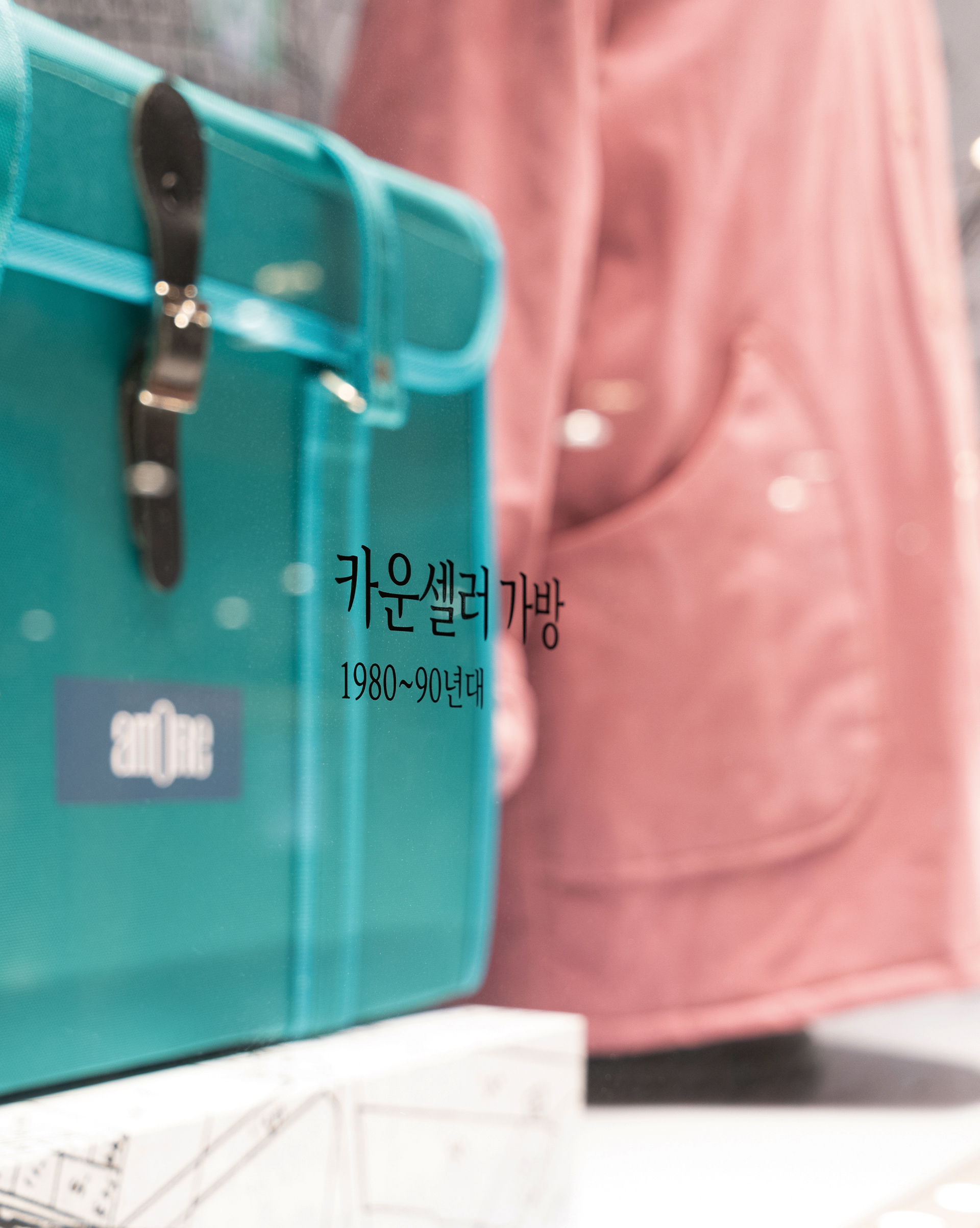
아리따부리 — 아모레퍼시픽에서 배포하는 무료 폰트입니다. 전통 명조의 구조에 현대적인 곡선과 섬세한 부리를 더한 우아한 본문용 세리프체
아리따 가족의 부리 쪽으로, 2012년에 착수해 2014년에 완성하고 2015년 1월에 무료로 풀렸습니다. 글꼴 디자이너 류양희가 맡고 안그라픽스 타이포그라피연구소가 진행했습니다. 여덟 번의 회의와 서른두 개의 스케치 시안을 거쳤는데, 본문 글꼴의 미덕인 보편성과 기업 글꼴에 필요한 개성 사이에서 균형을 찾는 과정이었다고 기록돼 있습니다.
목표는 분명했습니다. 기존 명조체의 예스러운 표정에서 벗어나는 것입니다. 그래서 글자 줄기를 부드럽게 휘고 획의 움직임을 유연하게 풀어, 손글씨의 운동감을 명조 구조 안에 넣었습니다. 파일에서 재어 보면 세로획이 가로획의 2.1배에 이르는데, 이 또렷한 대비가 단아하면서도 선명한 인상을 만듭니다.
굵기는 헤어라인부터 Bold까지 다섯 가지이고, 이 가운데 헤어라인은 국내에서 처음 시도된 굵기로 알려져 있습니다. 2015년 레드닷 디자인 어워드 타이포그래피 부문을 받았습니다. 긴 호흡의 본문을 겨냥한 서체지만 헤어라인은 획이 머리카락처럼 가늘어 작은 크기나 어두운 배경에서는 획이 사라질 수 있으니 큰 크기에서 쓰는 편이 안전합니다. 아리따 돋움과 마찬가지로 판매용 포장과 CI·BI 사용이 금지되고 인쇄물에는 출처 표기가 필요합니다.